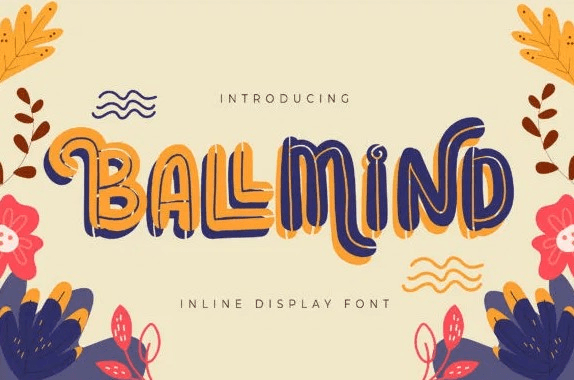
Ballmind Font
Ballmind - это игривый и веселый дисплей шрифта.
Независимо от того, ищете ли вы шрифты для Instagram или каллиграфические сценарии для DIY-проектов, этот шрифт превратит любую творческую идею в настоящее произведение искусства!
Ballmind - это игривый и веселый дисплей шрифта.
Независимо от того, ищете ли вы шрифты для Instagram или каллиграфические сценарии для DIY-проектов, этот шрифт превратит любую творческую идею в настоящее произведение искусства!